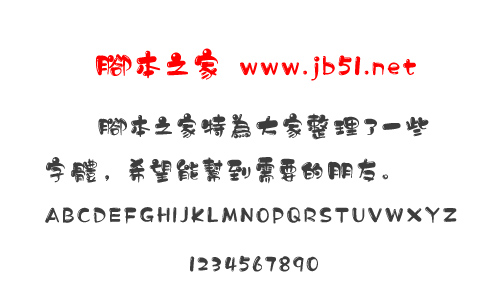
銳字溫帥小可愛繁是一款非??蓯酃郧傻淖煮w,在銳字溫帥可愛體的基礎上添加了高光,更加有立體感,銳字溫帥小可愛字形溫潤飽滿、親切乖巧,筆畫不拘一格、粗細對比協調、簡化變形有新意且不失識別性,營造了一種輕松歡快、充滿趣味性的氛圍??梢詮V泛應用于制版印刷、產品包裝、平面設計、藝術設計等行業(yè),需要在繁體輸入法模式下使用,歡迎大家前來下載。